我们从小就能够听到很多“别人家的孩子”的故事,他们往往学习成绩好,聪明活泼。而且基本上都会有一个特点,那就是字也写得相当漂亮。他们在学校里被老师同学们称之为学霸,写得一手好字的他们也因此被大家所喜欢。
娱乐圈中也有一些在学习成绩上较为突出的优异人才,比如大家所熟知的国民妹妹——张子枫。张子枫在演艺圈中尽管很忙碌,但也从来没有忘记自己的学业。2020年以河南省艺考第一名的成绩顺利拿到了北京电影学院的入场券,最后以面试第三名的成绩进入北电。
张子枫“手写卡片”火了,字迹一笔一划工整清晰,难怪是北电学霸
在一次综艺节目的后台,记者去采访张子枫时发现她在翻看自己的笔记,从图片上看张子枫的笔记,果真是非常详细,看得出来她对学习还是十分上心的,真学霸无疑。
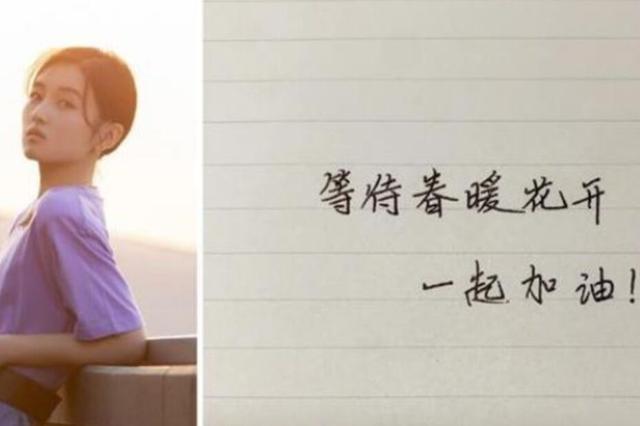
疫情期间,张子枫在网络上发了一张手写卡,上面写着:“等待春暖花开,一起加油”,手机卡上的字迹工整,一笔一划。这整洁的字迹也算是娱乐圈中一股清流的存在。同样,在高考中这样的字迹是十分受阅卷欢迎的。
作为一名高中生,在平常的学习和考试中该注意哪些写字的规范要点呢?
1、保持卷面的干净整洁
高中生在答卷时需要注意保持卷面的干净和整洁,同时在写字的时候要注意美观大方。在下笔前需要想好自己所要表达的内容,切记在写字的过程中不要勾勾抹抹,容易影响卷面的呈现效果。进而给阅卷老师留下不好的印象。
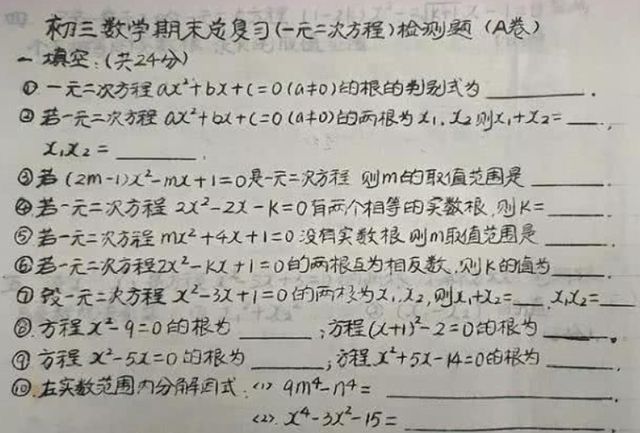
试卷上出现太多的涂抹修改现象,反而会反映出这名同学在答题时没有高度的专注,思路上十分不清晰。所以在平常的写字中,就需要培养自己良好的书写习惯,这样才会在考试中有很大的优势。
2、写字规范
高中生在写字的时候很容易炫耀自己略带狂草的字迹,很多时候写的字都是连笔的,很难让阅卷老师看出写了什么内容。但学生自己却认为这样的自己十分的潇洒帅气。
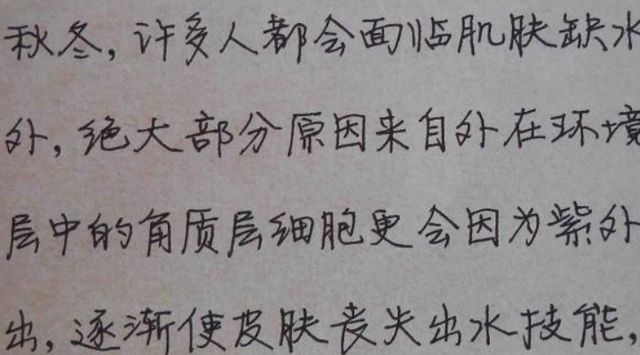
不过连笔的字的确不适合高中生,并且在考试中也很难让阅卷老师辨认,尤其是语文的诗词默写这样的题目,连笔字出错就会被判定整个句子错了,最终会导致自己失分。
3、注意字体的大小
高中生在答题的过程中需要注意好自己字体的大小,有些同学在答题的时候字体写的过大,甚至于都靠到了答题卡的边框处,而这种答题方式往往是很“危险”的,因为在阅卷的时候是通过扫描的方式传输到电脑中,超过答题边框的部分阅卷老师是看不见的,这就会导致答题不完整而失分。当然,字迹过小也会增加阅卷老师工作量。
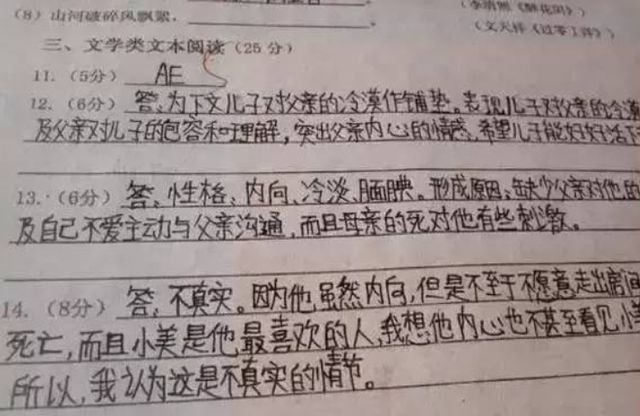
4、写字时有耐心
高中生日常的学习压力是比较大的,并且课程也很多,需要花大量的时间在学习上。所以在写字的时候难免缺少耐心,注重速度,写出来的字就比较“飘忽”。
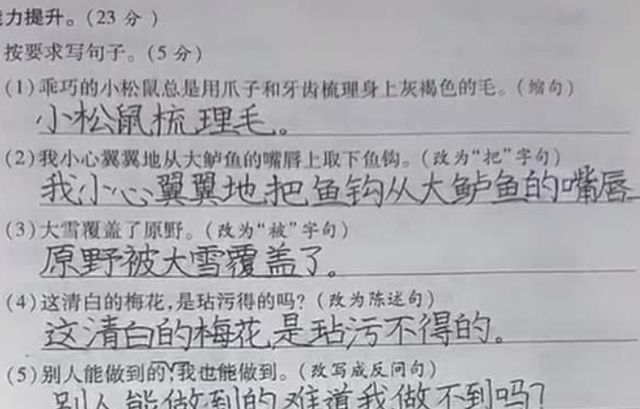
在日常的学习中,高中生的课业繁重,没有过多的时间用来练习写字,所以更要利用好平时写作业的机会,多一些耐心,稳住自己的学习状态。
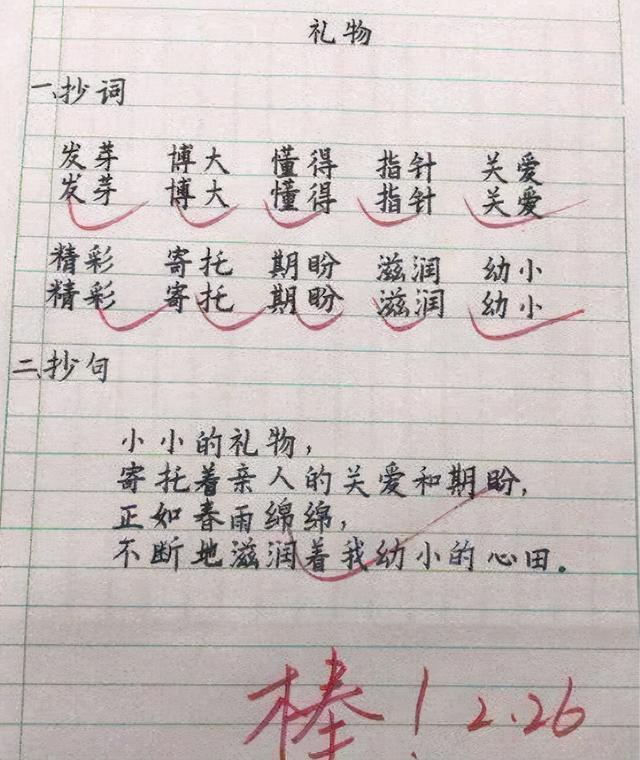
书写对于我们每个人都是十分重要的,不仅在考试中可以帮助我们获取高分,对今后的工作和生活都会有很大的帮助。毕竟字如其人这句话是有道理的,工作中或许还会因为字写得好,而被人另眼相待。
很多童星平时拍戏都非常的忙,可他们依旧能够做到每方面都很出色,这究竟是为什么呢?
其实除了张子枫之外,娱乐圈中还有很多很优秀的学霸们 ,他们不光成绩优秀,事业上也平衡的非常好。这不免就会让大家产生疑问,他们平时那么忙,学习怎么还会保持的这么好,写字也这么好看,哪里来的时间练习呢?
他们其中大部分人虽然要忙于拍戏,但是他们不会把自己的功课落下。尽管不能去学校上课,但都会请专门的私教老师来给自己进行补习。明星群体大都是高收入,所以他们会专门请一些名师来辅导自己的功课,这样成绩也会比一般学生提升的快很多。在拍戏的间隔,他们也会抽空回到学校参加考试集训,这样是不会耽误学习的。
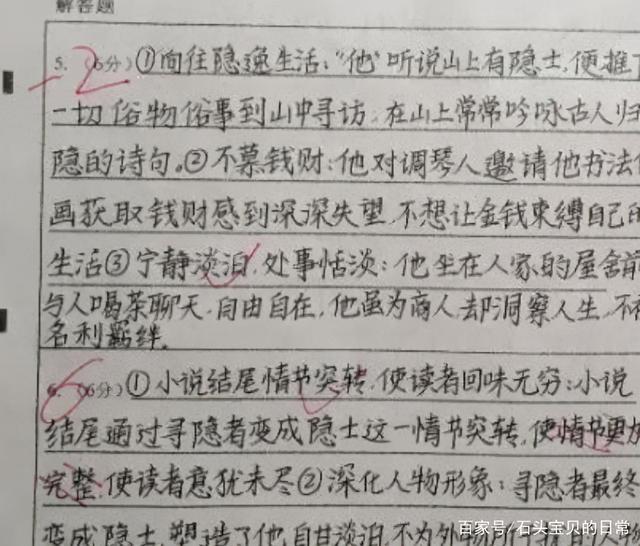
总结:
明星们比普通学生要更加的努力和自律。明星本身的曝光度就决定了他们在生活中需要尽量克制自己的行为,更加努力的学习向上。明星们一般考大学的途径都是参加艺考,主要考察的科目是与艺术相关的门类,在文化课上没有过高的要求,所以相对来说他们的成绩更好一些。
尽管艺考不能同高考划等号,但是在艺考中能够取得前几名的成绩也是非常不容易的事情,有一些童星们在文化课上也表现的十分优异,所以他们还是很优秀的。